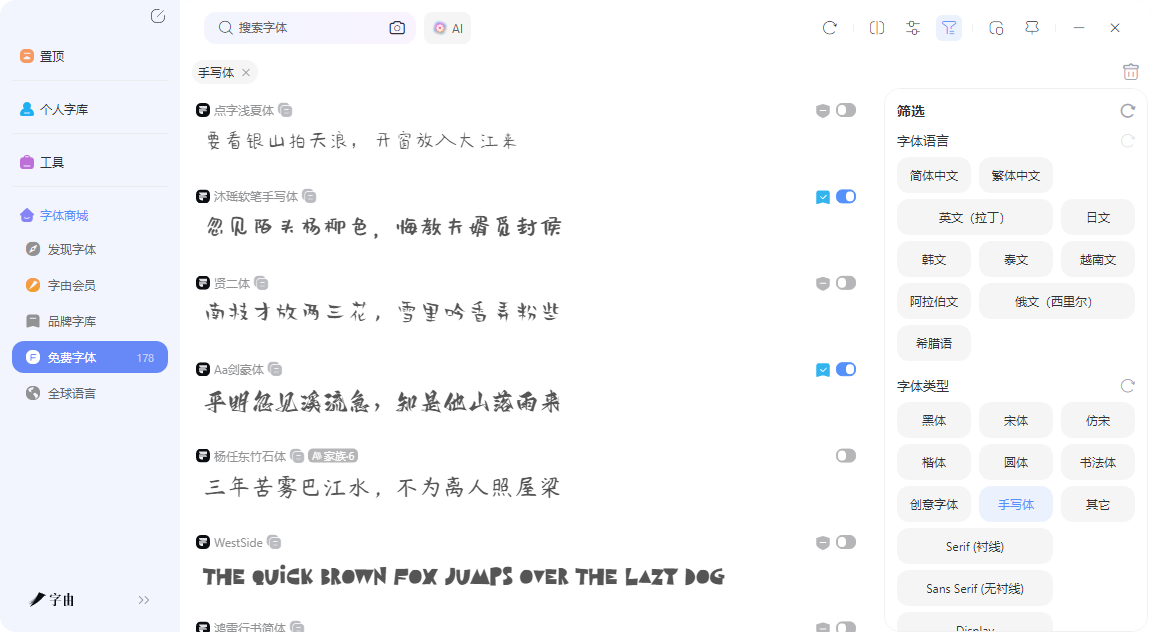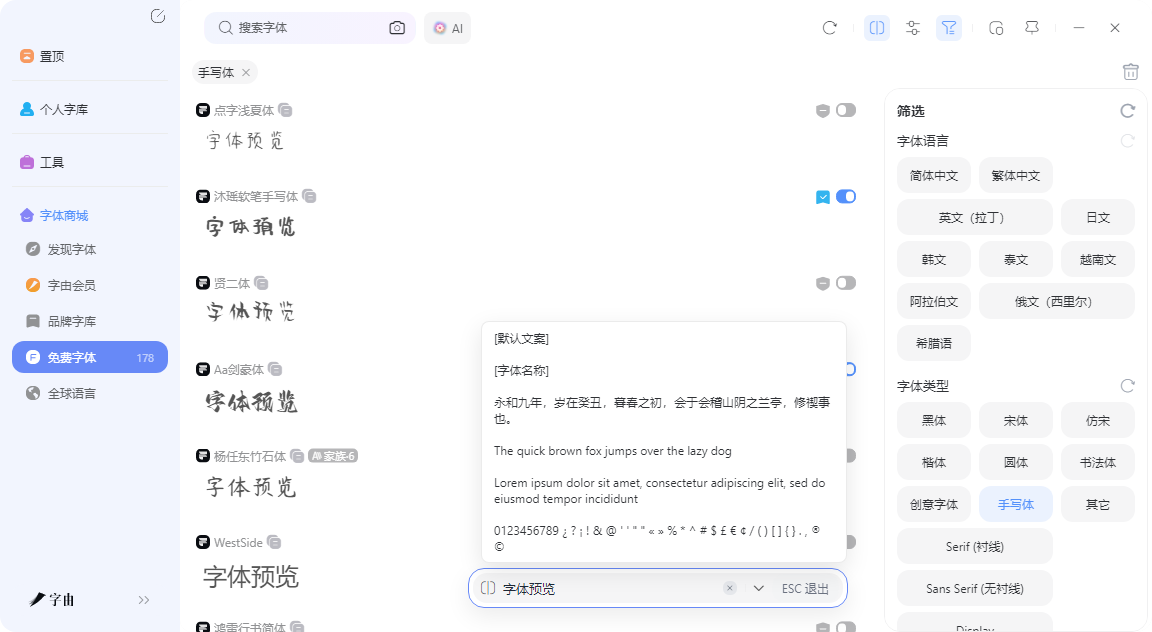
中文手写字体下载去哪找?这个网站里的资源免费又好看
打开PS,想给海报加一行手写感的标题,翻遍了字体列表,不是“方正静蕾简体”就是“叶根友手写体”。不是不好看,是大家都在用。做出来的东西跟别人的放在一起,一眼看过去分不清是谁的。想找点不一样的中文手写字体,上网搜了半天,要么要收费,要么不知道能不能商用,要么下载了一堆装完发现不好看,还得一个一个删。其实找中文手写字体这件事,不需要这么折腾。字由这个平台,把找字体、试字体、用字体这件事全包了。接下来可以看看在字由里怎么操作。
1、不用到处搜,上万款字体都在一个库里
打开字由客户端,左侧筛选栏里找到“字体类型”,勾选“手写体”。一瞬间,上百款中文手写字体列在你面前。它们不是那种千篇一律的“电脑手写”,而是各有各的性格。
钢笔手写类:笔画干净利落,像用钢笔在纸上快速书写。适合文艺风海报、手账、书信体设计。比如“字由芳华体”,笔画纤细飘逸,带着一种不经意的随意感。
毛笔手写类:有墨迹的浓淡变化,笔触更有力量感。适合国潮风、品牌标题、中式包装。比如“字由颜楷”,虽然是楷书,但手写感很强,不像印刷体那么死板。
儿童手写类:笔画圆润、歪歪扭扭,像小朋友写的字。适合儿童产品、教育类设计、亲子主题。
涂鸦手写类:带有个性化的装饰元素,比如连笔、花体、墨渍效果。适合潮牌、音乐节海报、年轻人社群的内容。
每一款字体都有实时预览功能。输入你自己的文案——比如你的品牌名或者一句slogan——预览框里立刻显示这款字体的真实效果。不用先激活再试,看不上直接翻下一篇。
挑选中文手写体的三个实用技巧
面对上百款手写体,怎么快速找到最适合的那一款?三个技巧供你参考。
• 技巧一:先定场景,再选风格。 做儿童绘本,优先看“儿童手写类”;做国潮海报,直奔“毛笔手写类”;做小清新手账,在“钢笔手写类”里翻。字由的分类已经帮你筛掉了一大半不相关的选项。
• 技巧二:用真实文案预览,别被模板迷惑。 很多手写体在展示图里很好看,但换上你的品牌名或slogan后,字间距、连笔效果可能完全不一样。在预览框里输入你要用的真实文字,再看效果,这才是最终的样子。
• 技巧三:对比字重和可读性。 有些手写体太潦草,远看根本认不出写的是什么。做标题还好,做正文或者需要清晰传达信息的设计,建议选笔画相对规整的“钢笔手写类”或偏楷书的手写体。字由预览时可以调节字号大小,缩小到实际使用尺寸再判断可读性。
4、不知道选哪款?可以试试筛选功能
字由里每款字体右侧都显示“使用次数”。这个数据是基于平台上所有设计师的真实使用行为统计的。排在前面的,说明被大量项目验证过,跟着选基本不会错。如果你想找的是小众、还没被用烂的手写体,可以按“热度从低到高”排序。那些藏在库深处、用的人少的中文手写体,往往能给你的设计带来意想不到的惊喜。